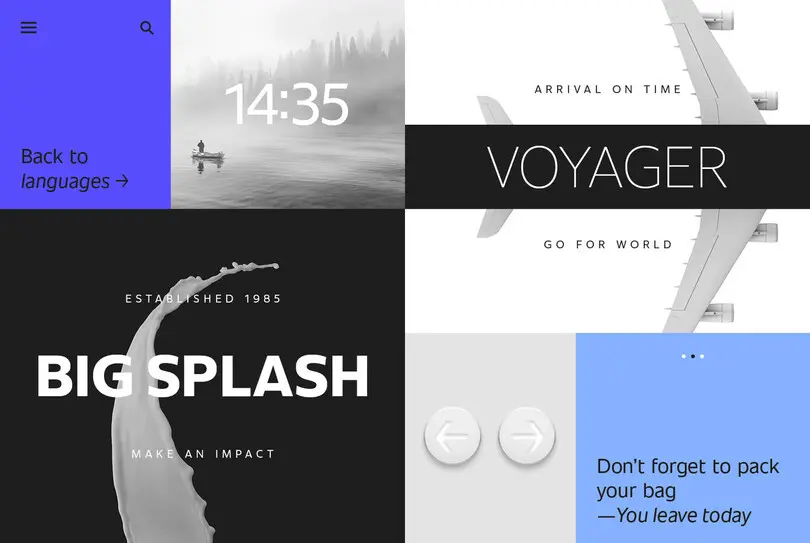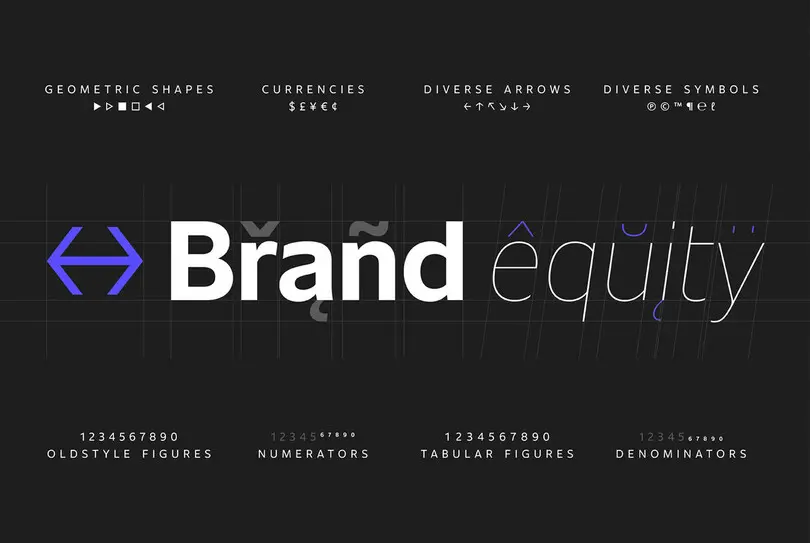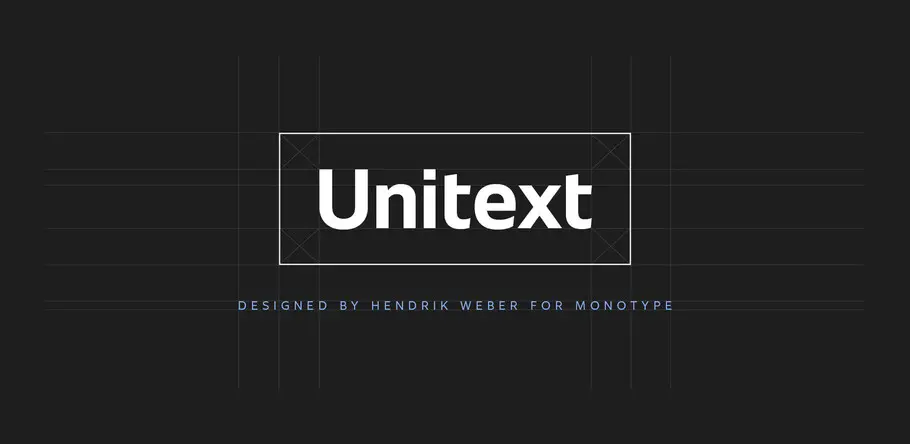
Unitext – perfektes Zusammenspiel von ökonomischer Spationierung und offener Zeichenform.
Hendrik Webers Unitext™ ist eine klare und effiziente serifenlose Schrift, die sorgfältig auf die Anforderungen des Branding-Designs zugeschnitten wurde. Inspiriert von aktuellen Designtrends und dem Feedback hunderter Marken, bieten die beiden neu erschienenen Sans-Serif-Familien Unitext und Madera einen Mix aus Moderne und klassischer Anmutung. Beide wurden mit dem Ziel entworfen, Unternehmen und Marken dabei zu unterstützen, ihre Stimme markant und lesbar zu visualisieren, vom Kleingedruckten bis zur Beschilderung, im Print-Bereich und im digitalen Umfeld.
Unitext™, entworfen vom den Agentur-erfahrenen Monotype-Designer und Leiter des Berliner Studios Hendrik Weber, wurde mit dem Ziel entwickelt, sowohl visuelle Gestalter als auch Marken-Berater zu begeistern. Die Schrift ist in 7 Strichstärken lieferbar, jeweils mit Kursiven sowie einem umfangreichen Zeichenvorrat mit diversen Ziffernsätzen, Sonderzeichen und stilistischen Alternativen, die gerade im Corporate Design wertvolle Dienste leistet. Die Familie ist so konzipiert, dass sie nicht nur sämtliche Kontaktformen in der Kommunikation mühelos meistert, sondern zusätzlich eine stilvolle Wiedererkennbarkeit von Marke oder Unternehmen garantiert.
Unitext eignet sich besonders für den Einsatz in der Reise- und Freizeit-Branche, für Werbung, Logos, Text und Leitsysteme
Die Unitext-Familie lässt sich als klare, universell, zeitgemäße und authentische Schrift charakterisieren. Die Kombination grotesker und humanistischer Zeichenformen ergibt eine außergewöhnliche Mischung aus verdichteten Abständen und offenen Letterformen, perfekt für eine plakative Gestaltung (Logos, Displays) wie auch für Mengentext.
Für Unitext hatte Hendrik Weber von Anfang an ein einfaches, kompaktes und gleichermaßen freundliches Schriftbild im Sinn, sozusagen als »natürliche Stimme« einer Marke oder eines Unternehmens. Unitext wird in sieben Schnitten (Hairline bis Black) plus Kursive angeboten. Jeder Font enthält als besonderen Service, neben Brüchen und diversen Ziffernsätzen, geometrische Symbole, Pfeile und weitere Raffinessen.
„Oft hören wir von Marken, dass sie für Text und Logos, über alle Touchpoints hinweg, gerne eine einzige Schriftart einsetzen möchten, wobei das mit vielen traditionellen Schriften nicht wirklich gut funktioniert.“ Erzählt Hendrik Weber aus seiner Beratungspraxis.
„Diesem Ansatz folgt Unitext, die ich so entworfen habe, dass sie Marken und Unternehmen, die ein dynamisches, kompaktes Schriftbild wünschen, eine einheitliche Stimme in allen Kanäle verleiht, wo die Kunden anzutreffen sind.“
Unitext wird in sieben Schnitten (Hairline bis Black) plus Kursive angeboten. Jeder Font enthält als besonderen Service, neben Brüchen und diversen Ziffernsätzen, geometrische Symbole, Pfeile und weitere Raffinessen.
Empfohlene Schriftpaarungen
Der moderne, Business-bezogene Sans-Serif-Charme von Unitext macht sie zum idealen Partner für kontrastierende Schriftstile. Unitext harmoniert am besten mit Slab-Serif-Schriften und Klassikern wie Aptifer™ Slab, Bembo® Book, ITC Berkeley Old Style®, PMN Caecilia®, Sabon® Next and Ysobel™ typefaces.